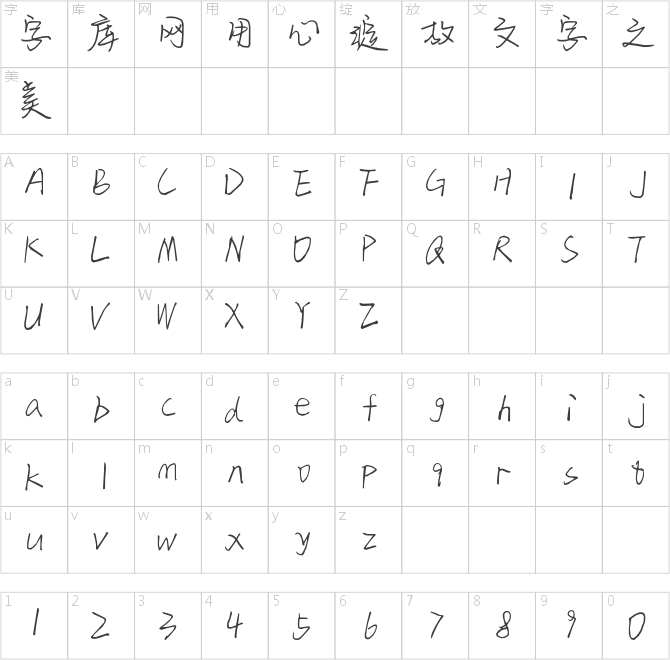
伯樂俏皮體 詳情頁
字體名稱: 伯樂俏皮體
伯樂俏皮體
伯樂俏皮體介紹
伯樂俏皮體字體字庫是一款讓人賞心悅目、百看不厭的中文字體,適合各類廣告和產(chǎn)品包裝設(shè)計應(yīng)用,字體大小3.38MB,格式為ttf字體,上傳用戶是123123aaa,作者/版權(quán)方為伯樂字庫